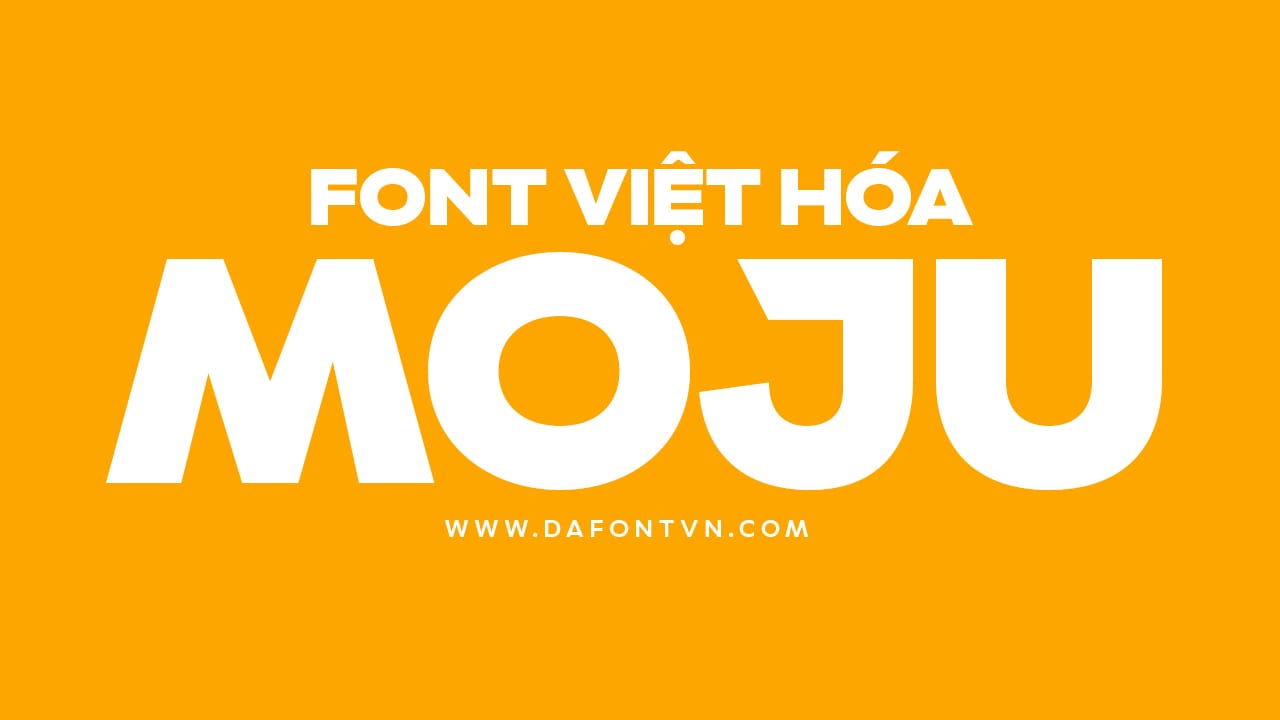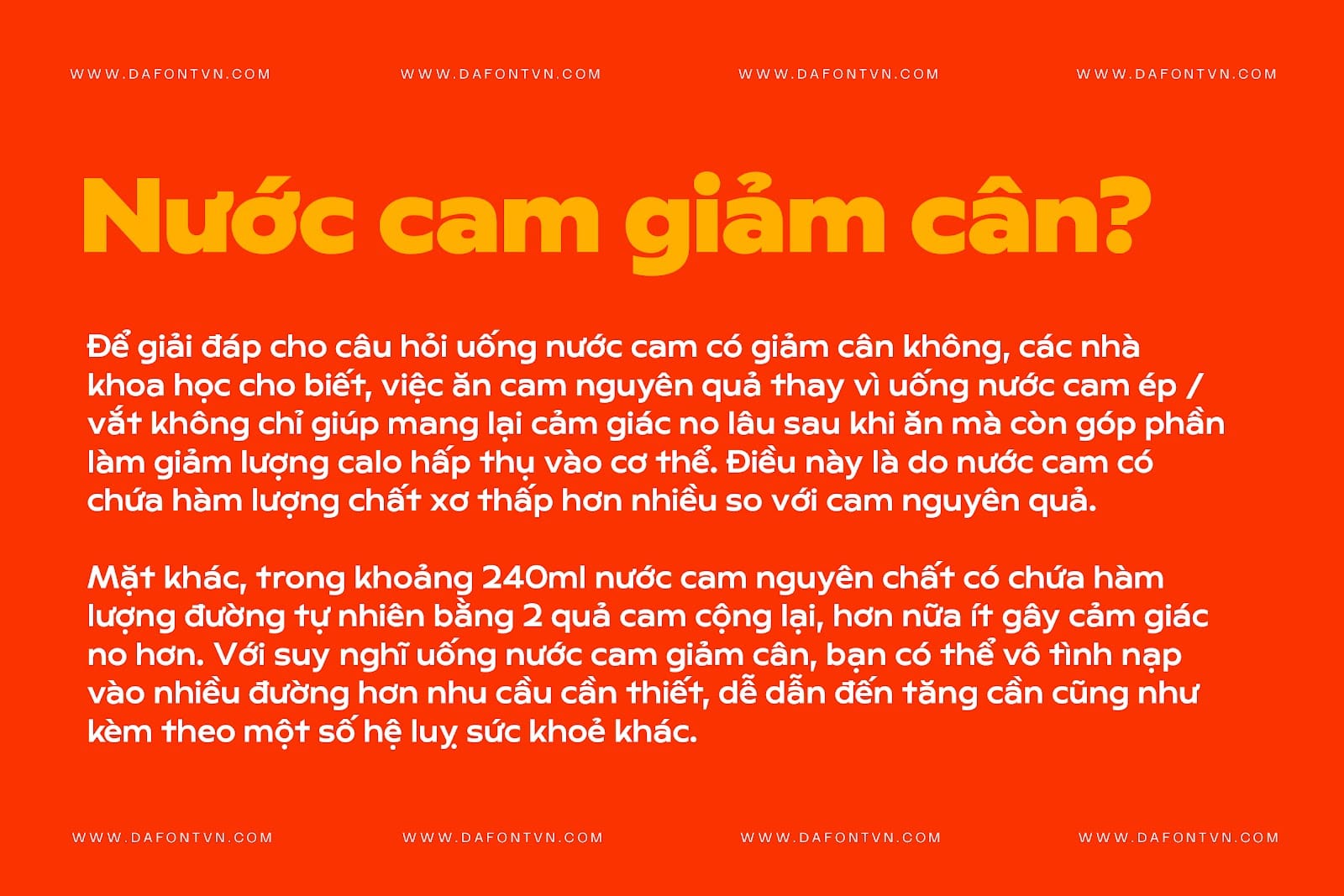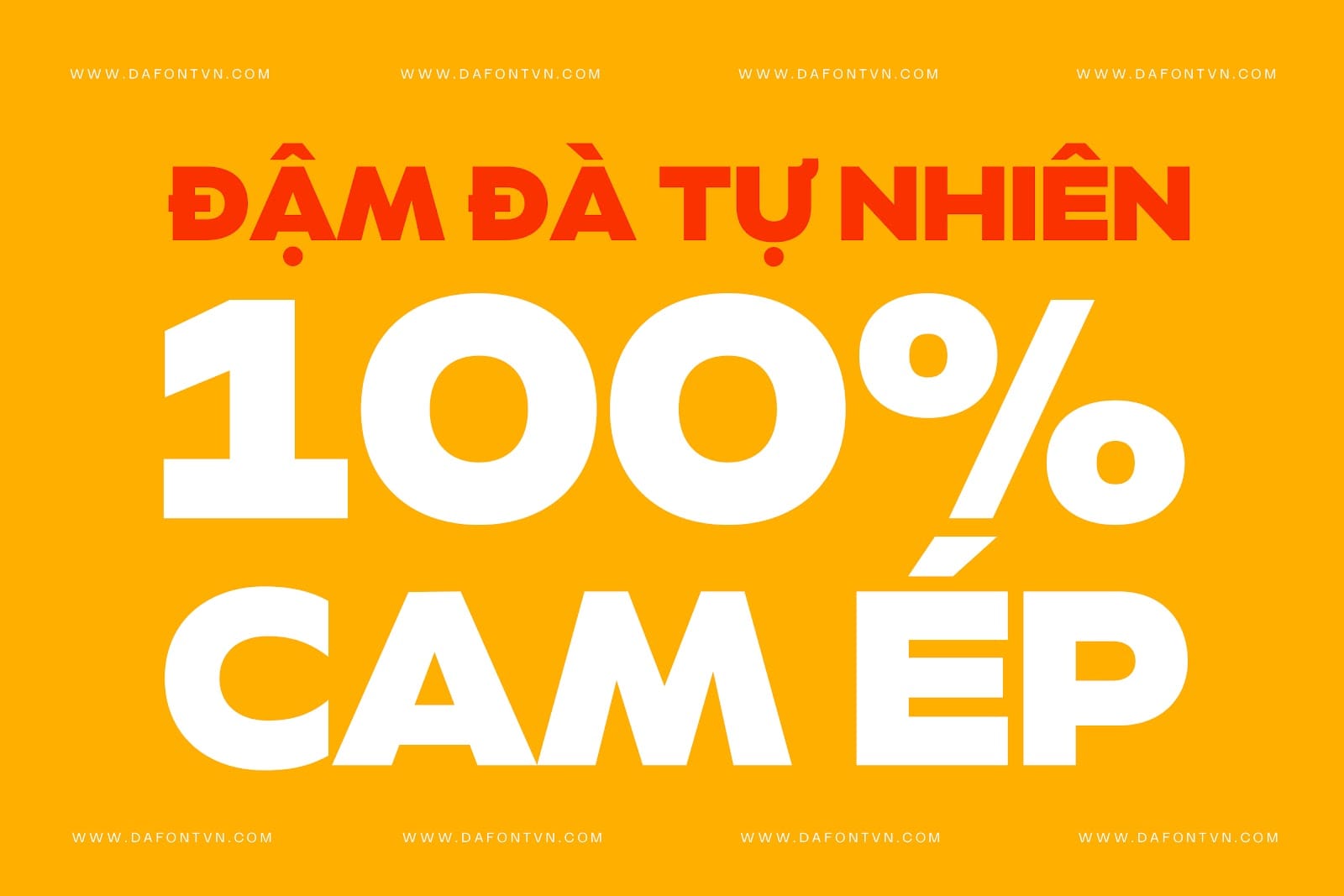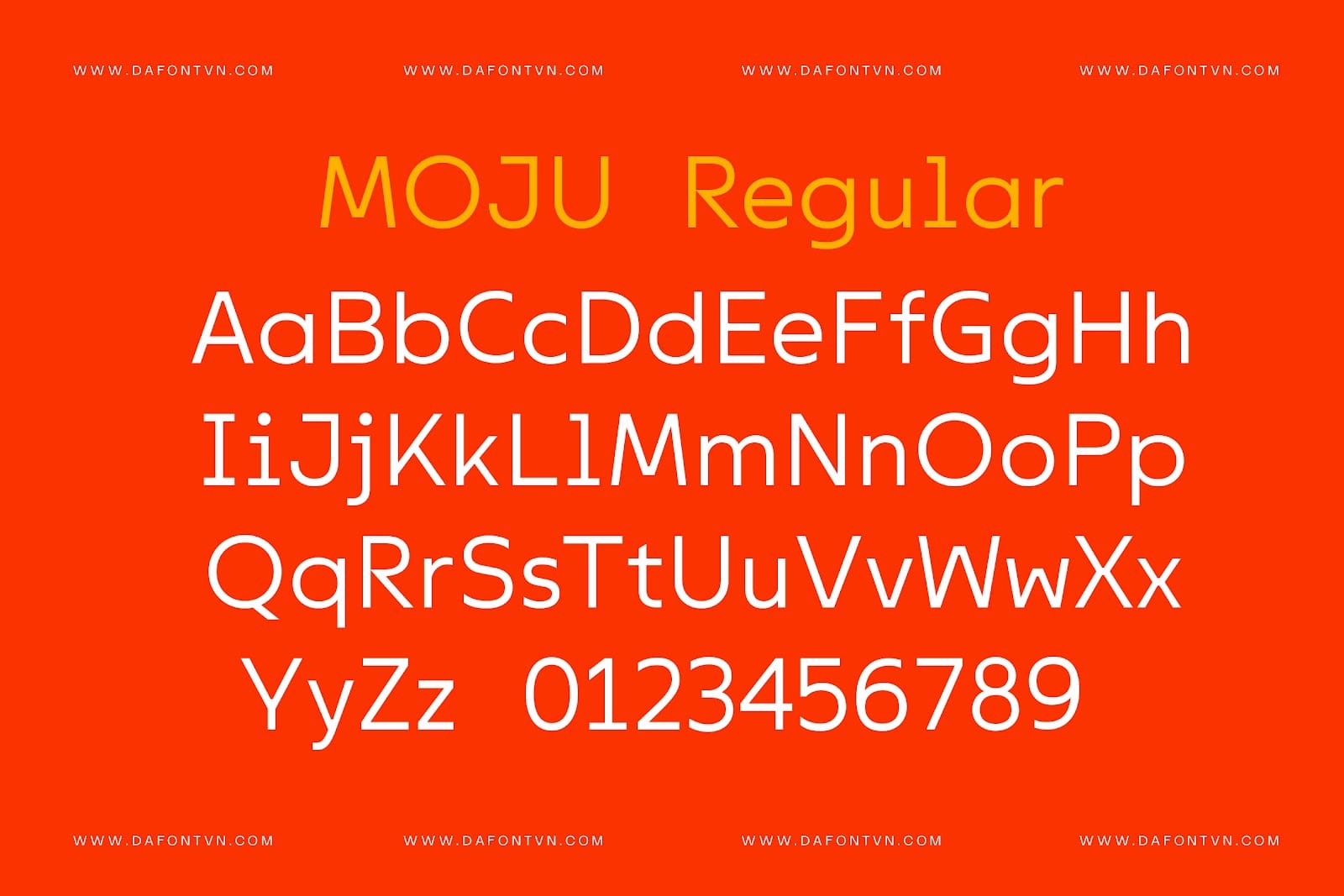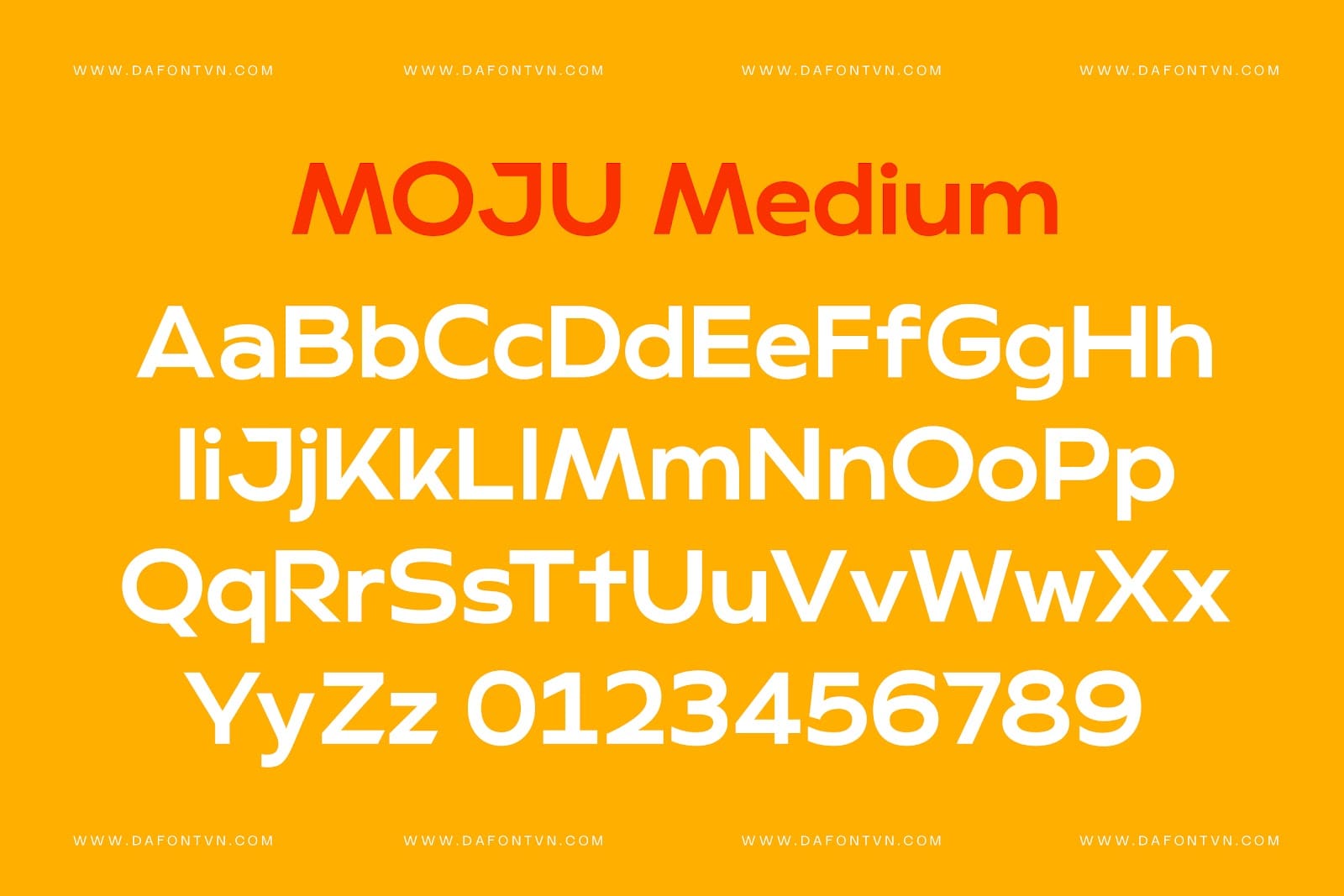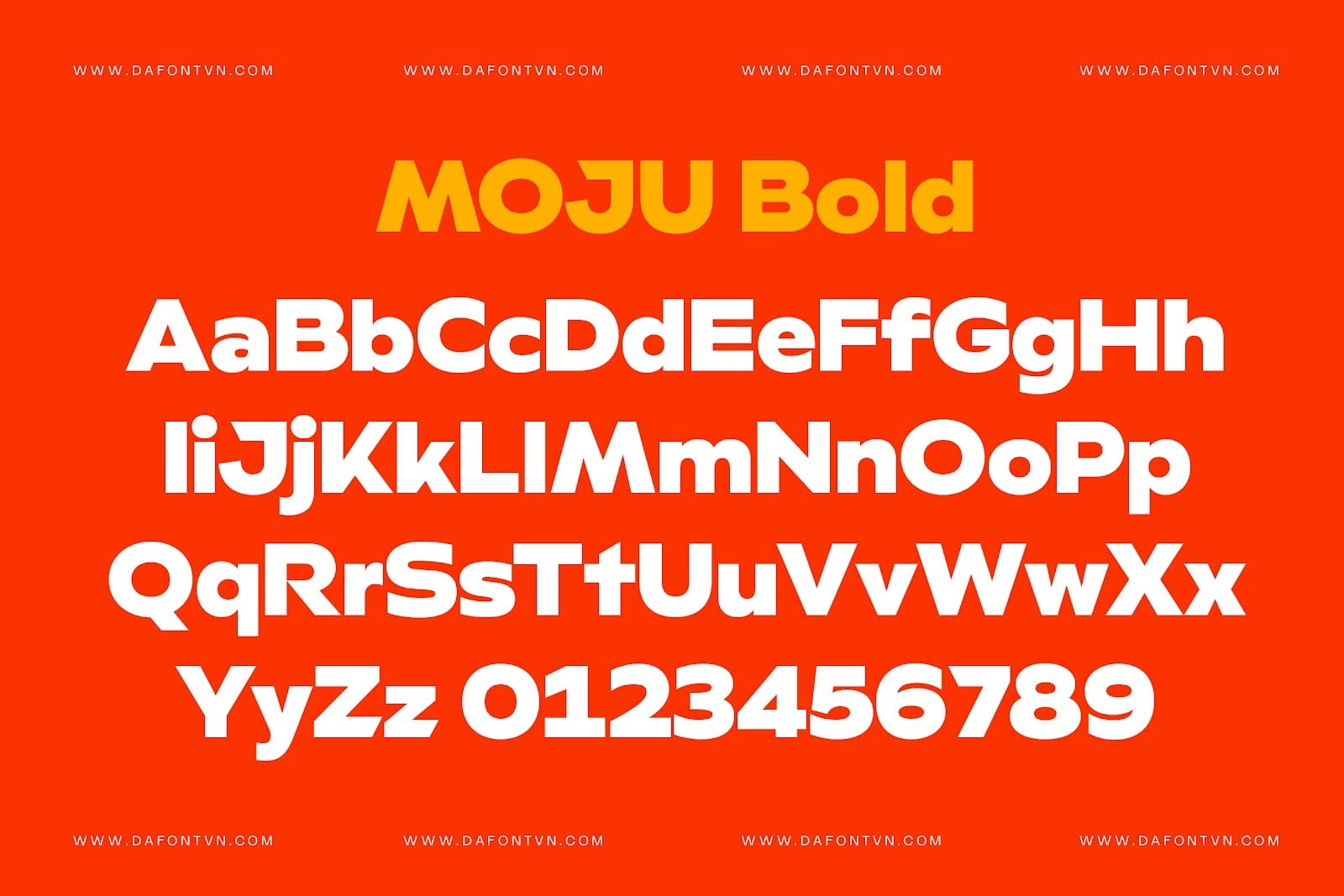
Font MOJU Việt hóa (3 font) – Font thương hiệu
MOJU là kiểu chữ được thiết kế bởi Colophon, nằm trong bộ nhận dạng thương hiệu mới của MOJU. Đây là một thương hiệu đồ uống đến từ Vương Quốc Anh.
Bộ font chữ MOJU gồm 3 kiểu (Light, Medium và Bold), bộ font này được sử dụng trong tất cả các sản phẩm thiết kế của MOJU từ logo, bao bì, túi xách, website, quảng cáo…
Dựa trên đặc tính thương hiệu năng lượng cao của MOJU, khái niệm thiết kế tổng thể là gợi lên sức sống của dòng sản phẩm của MOJU thông qua kiểu chữ. Nét trên cùng của chữ “J” trong logomark MOJU là điểm khởi đầu cho độ dày đậm, với các đường cắt góc tương tự nổi bật xuyên suốt kiểu chữ ở các dạng như “Q” “t” và “Z”.